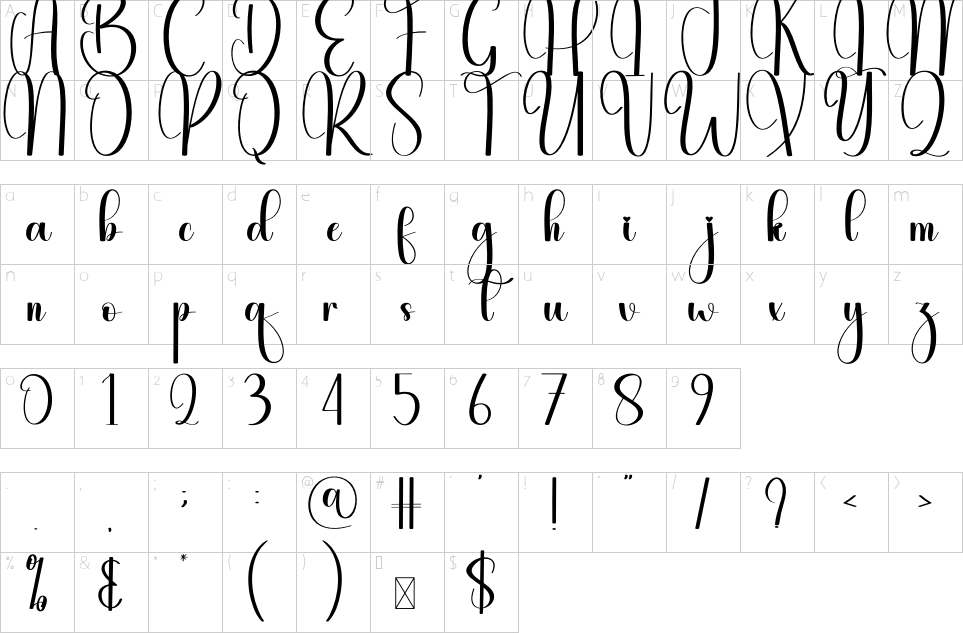
A fonte Archery oferece uma experiência visual agradável e envolvente, perfeita para designers e criadores de conteúdo que buscam uma tipografia moderna e elegante. Desenhada por William Jhordy, Archery foi projetada para dar destaque a seus trabalhos, seja em ambientes digitais ou impressos. Com seu design clean e arredondado, a fonte garante uma experiência de leitura confortável, especialmente em aplicativos para Windows e Mac. Seu design é uma ótima escolha para projetos em diferentes formatos, desde pequenas etiquetas até grandes logotipos. Com a fonte Archery, você terá mais um recurso para personalizar seu trabalho de design, garantindo que seu projeto brilhe com uma aparência única e sofisticada. Seu baixado 297 vezes, sugere que a fonte já foi apreciada por muitos designers. Baixe já e faça sua marca brilhar com a Archery.